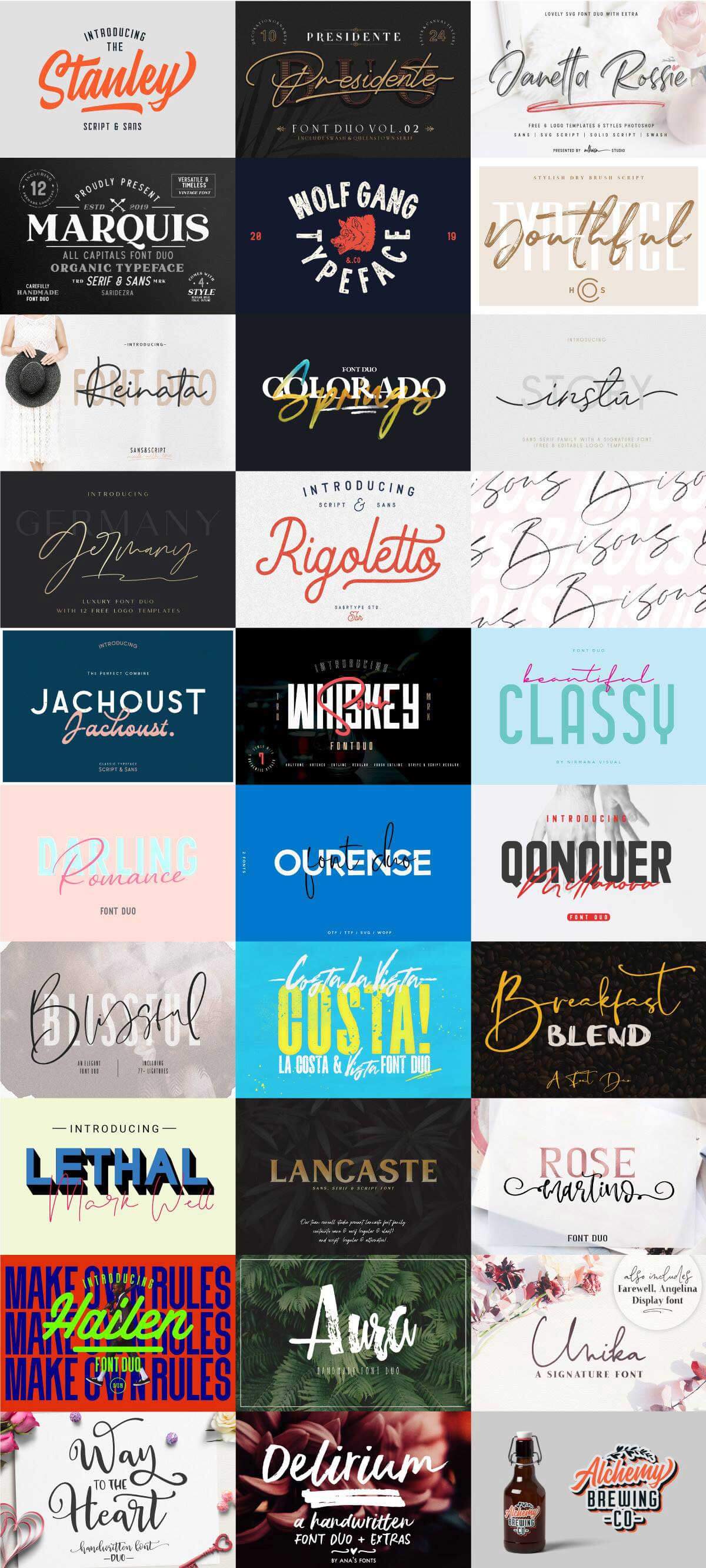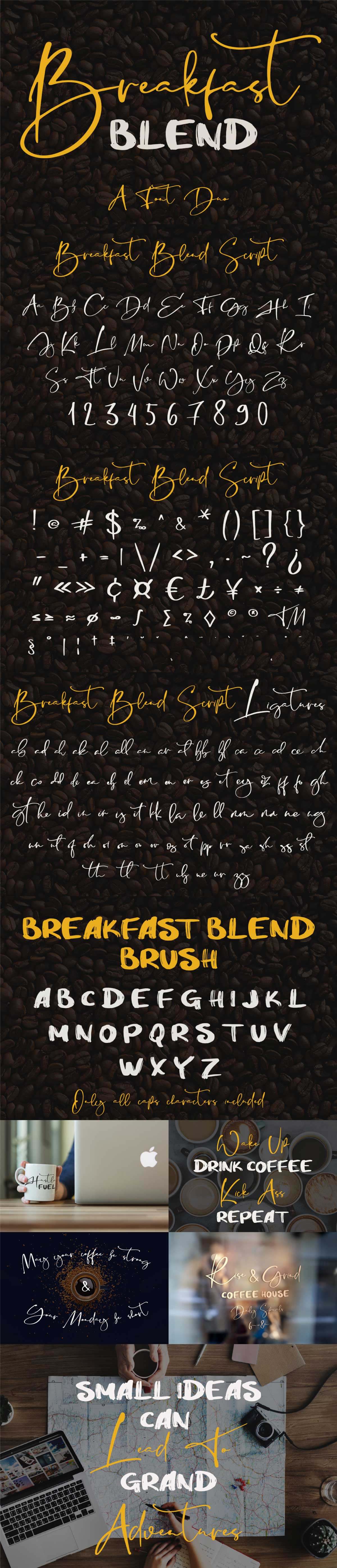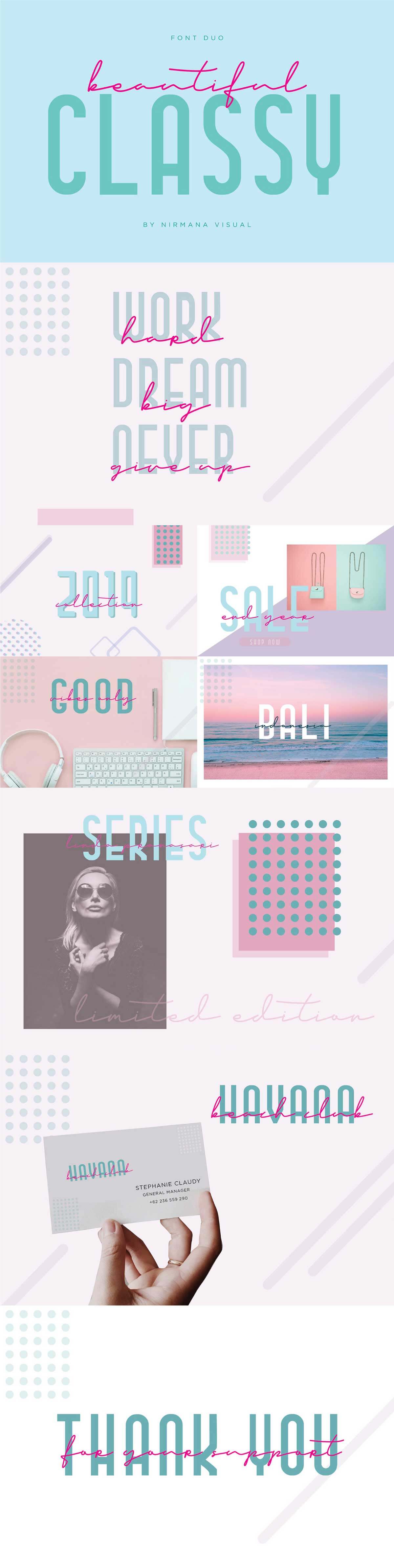
Pixel Surplusでは、ペアリング済みフォントを29セット集めた「The Dynamic Font Duo Bundle(ザ・ダイナミック・フォント・デュオ・バンドル)」が販売中です。
あらかじめ書体の組み合わせが用意されているので、フォント探しにかける時間を節約できます。
「The Dynamic Font Duo Bundle」の気になる中身
今回のバンドルの中で、私が特に気になるフォントはこちらです。
Germany – Dharmas
細めでクリーンな印象のサンセリフ体と筆記体のセット「Germany」。筆記体のウェイトも2種類用意されていて、デザインにこだわりたい方には見逃せないセットです。
Classy Beautiful – Nirmana Visual
「Classy Beautiful」はx-heightが極端に低いサンセリフ体と筆記体のセットです。サンセリフ体を大きく使い、その上に筆記体を小さな文字でのせるとバランスがよく見えます。
Breakfast Blend – Pixel Surplus
Pixel Surplusオリジナルの「Breakfast Blend」。かわいい雰囲気のゴシック体と筆記体のセットです。現在(2019年3月4日)はPixel Surplusでしか購入できません。
このほか使えるフォントの組み合わせばかり合計29書体セットを収録しています。この記事で紹介できなかった書体はぜひ詳細ページから確認してくださいね。